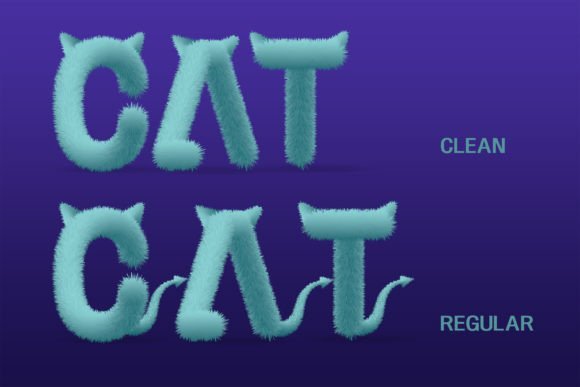
Cat Font
Cat Font – الخط المثالي لعشاق القطط والمصممين المبدعين!
أضف لمسة من المرح والإبداع إلى تصاميمك مع Cat Font، الخط الفريد المستوحى من جمال وأناقة القطط. يتميز هذا الخط بتصميمه الأنيق والمرن، مما يجعله مثاليًا للمشاريع الفنية، والشعارات، والبطاقات، والتصاميم الرقمية والمطبوعة.
???? مميزات الخط:
✅ تصميم فريد مستوحى من القطط
✅ يدعم الأحرف الكبيرة والصغيرة
✅ مثالي للعلامات التجارية، والملصقات، والمحتوى الإبداعي
اجعل تصاميمك تنبض بالحياة مع Cat Font – الخيار الأمثل للإبداع والتميز! ????✨